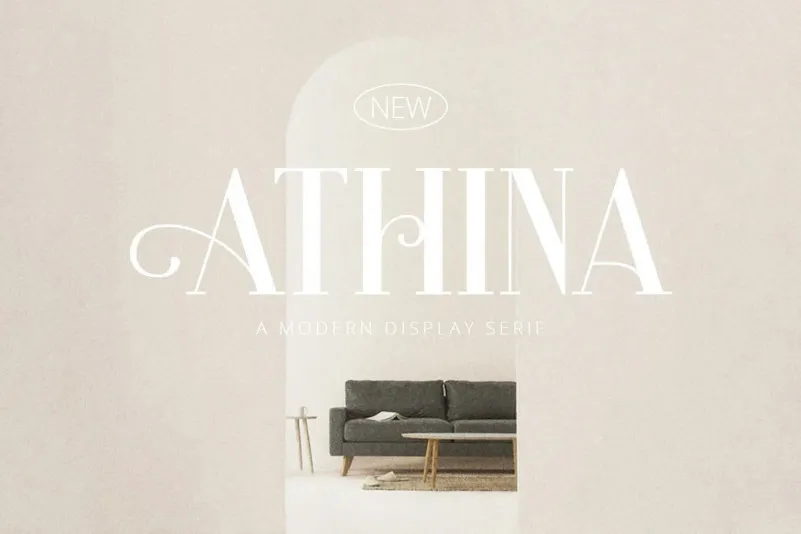
Athina Serif Font – Fonte Grátis
Athina Serif Font
A Athina Serif é uma elegante fonte serif que combina sofisticação com alegria, ideal para criações modernas e minimalistas. Com seu estilo infantil e feminino, essa font transmite beleza e suavidade em qualquer aplicação designística. Desenvolvida pelo Rillatype, Athina se destaca por sua versatilidade e originalidade. A fonte foi cuidadosamente projetada com swashes personalizáveis, permitindo que você personalize ainda mais seu design para criá-lo único e vibrante. É perfeita para aplicativos como logotipos, cartões de aniversário, moda, maquiagem, notas de recepção e muito mais. Com sua riqueza e graça, a Athina Serif traz uma dose adicional de personalização para os seus projetos visuais.